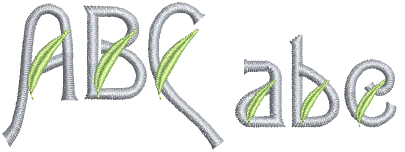
Schriftobjekte sind normalerweise einfarbig und bestehen aus einer einzigen Stichart. Die Wie digitalisiert-Verbindungsmethode kann jedoch benutzt werden, um Spezialschriftarten mit mehreren Farben oder besonderen Effekten zu erstellen. Wir werden jetzt diese Methode anwenden, um eine Variante unserer benutzerdefinierten Schriftart zu erstellen, indem wir jedem Buchstaben eine Verzierung hinzufügen.